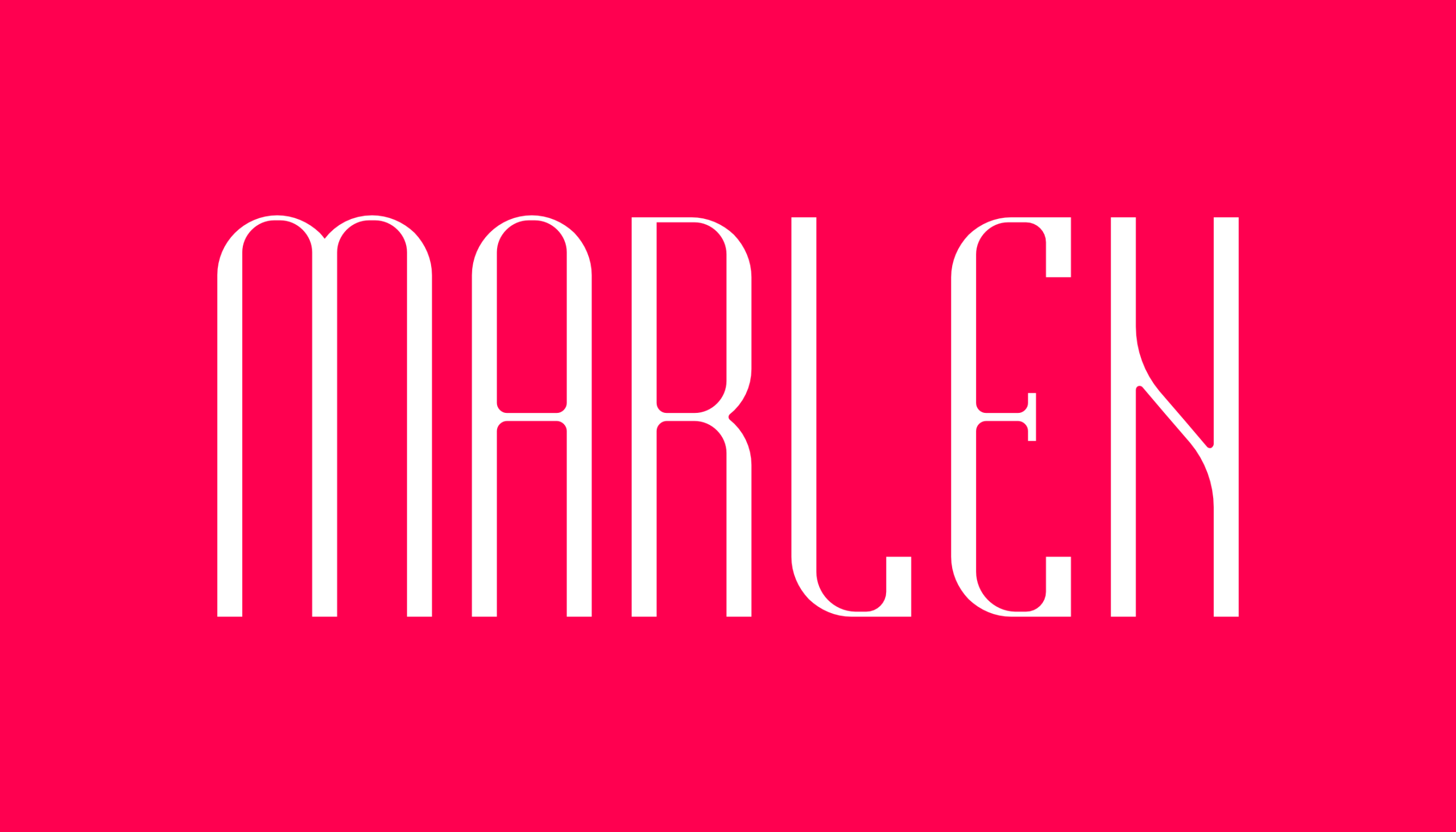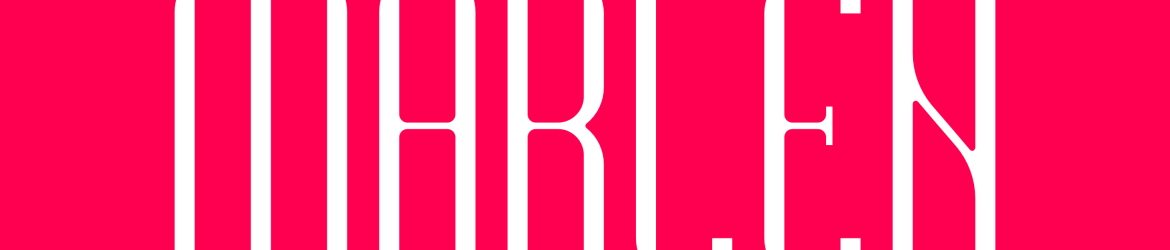
A fonte Marlen é uma criação inspirada no estilo Art Decó moderno, com influências de capas de revistas de moda e formas curvas da natureza. Ela se destaca pela sua fluididade e linhas geométricas elegantes, combinando o refinamento do design artístico com a simplicidade da arte de revista. Ideal para uso em elementos decorativos, Marlen é perfeita para personalizar materiais de marketing ou criar designs visuais sofisticados. Inspirada no designer Hamilton, esta fonte traz uma sensação de elegância e modernidade que se adapta perfeitamente a qualquer projeto que você decida trabalhar.